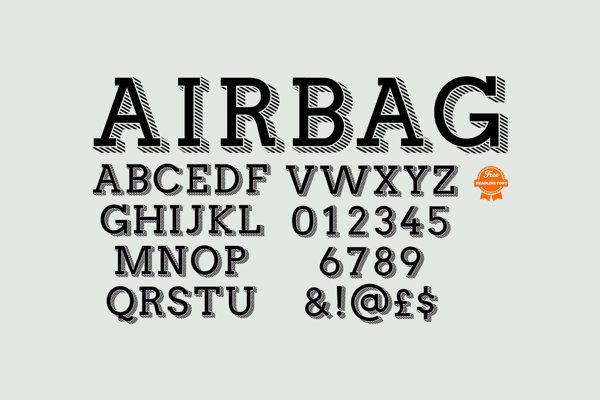
Vi Vi Vieeeeeeernes (parafraseando a Caelike xD) ya ha terminado otra semana y van once nada menos, el tiempo vuela. Para la súper-tipografía de hoy os traemos Airbag, diseñada por Simon Stratford, diseñador londinense con mucho arte que expone en su portfolio de Behance y que más de uno os dejará con la boca abierta. La tipografía Airbag es perfecta para cabeceras, diseños de cartelería. La versión gratuita cuyo pago será el de un twitt más que merecido no incluye la caja baja pero podréis adquirirla en la página del autor. Espero que os guste y recordad que los like y los follow ayudan mucho así que visitadnos en Twitter y Facebook. También nos podéis encontrar en Flipboard buscando nuestra revista El Arquitecto de Ilusiones.